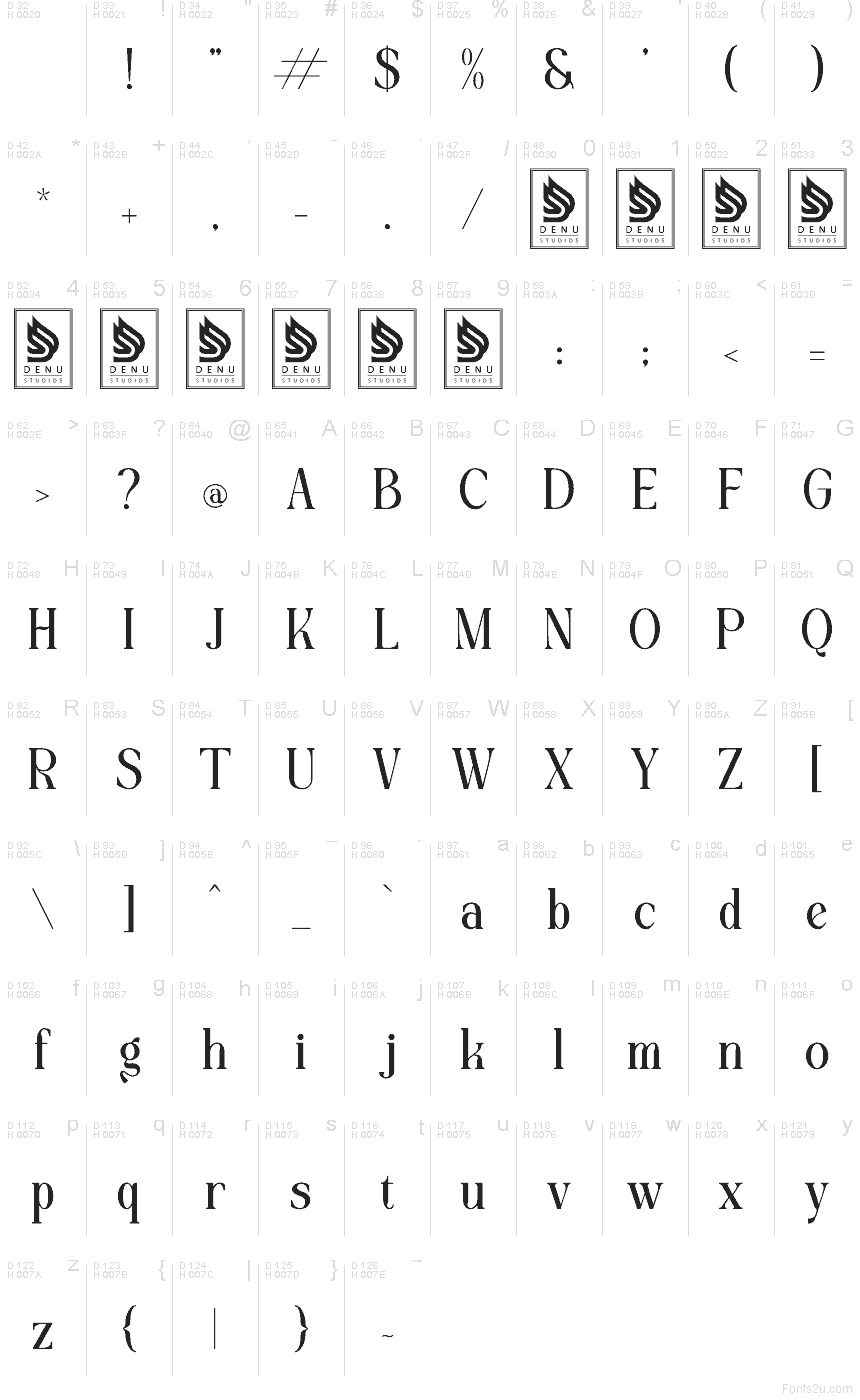
Nadeko de Denustudios es una tipografía serif gratuita de alto contraste con un estilo editorial y de moda inconfundible. Sus letras mezclan trazos finos como el cabello con pequeños remates afilados y curvas suaves, logrando una estética refinada pero no rígida.
Encaja perfectamente en cabeceras de revistas, packaging de boutiques, branding de belleza, portadas de libros y menús de restaurantes, donde ese contraste elegante puede sostener una línea corta por sí sola. Como tipografía gratuita, Nadeko también funciona muy bien en portadas, citas destacadas e iniciales tipo monograma, ya que sus formas tienen suficiente fuerza visual para lucir sofisticadas incluso en pocas letras.